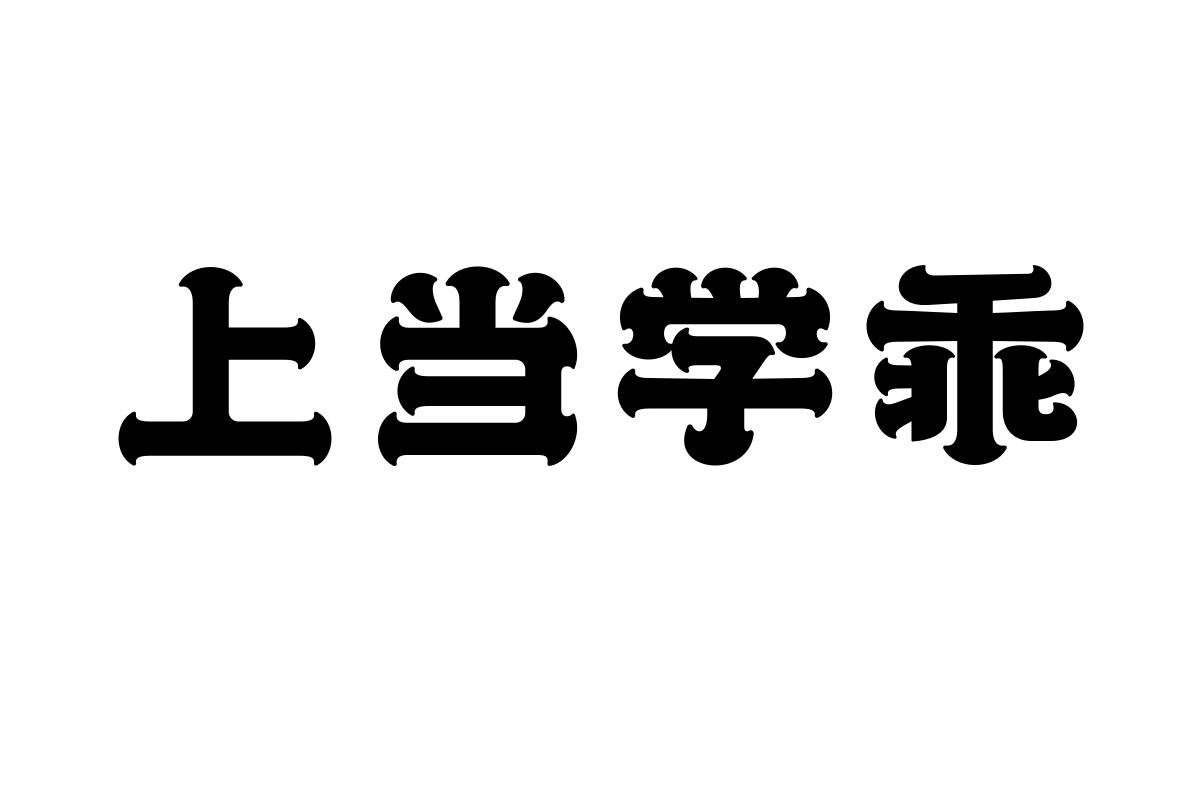
造字工房万象体是一款具有独特风格的字体。这款字体采用了现代的设计理念,结合了传统的书法元素,创造出了一种既有现代感又不失文化底蕴的字体。
造字工房万象体的字形结构紧凑而富有变化,笔画流畅自然,给人一种优雅而庄重的感觉。它的线条粗细不一,既有粗犷豪放的气势,又有细腻柔和的韵味,展现了汉字的独特魅力。
此外,造字工房万象体还注重字体的可读性和实用性。它的大小适中,易于阅读,适用于各种场合和用途。无论是用于印刷品、广告、设计作品还是个人签名,都能展现出其独特的风格和美感。
总之,造字工房万象体是一款独具特色且实用的字体,适合追求个性和艺术气息的设计者使用。